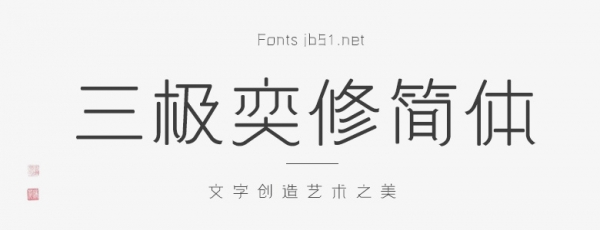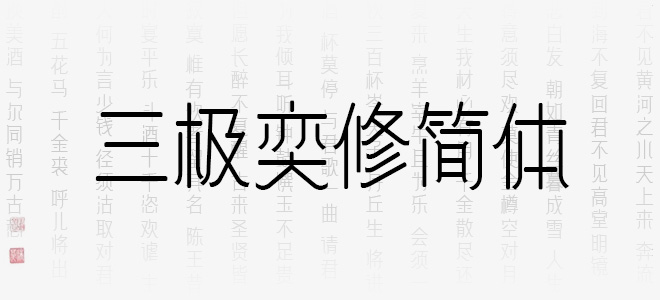
三極奕修簡(jiǎn)體字形清新,結(jié)構(gòu)嚴(yán)謹(jǐn),布白均勻,中宮偏大,重心一致。字型修飾得宜,恰到好處,整體規(guī)范而不失特色。嚴(yán)謹(jǐn)秀氣而從容和優(yōu)雅,讓人賞心悅目,百看不厭。可廣泛用于書(shū)刊、廣告、包裝、影視以及社交網(wǎng)絡(luò)個(gè)性化用字。適用于各類(lèi)便攜式屏幕的系統(tǒng)嵌入字體,以及傳統(tǒng)印刷媒介的標(biāo)題與正文排版。在品牌形象設(shè)計(jì)中作為logo設(shè)計(jì)性文字視覺(jué)效果更佳。
三極奕修簡(jiǎn)體